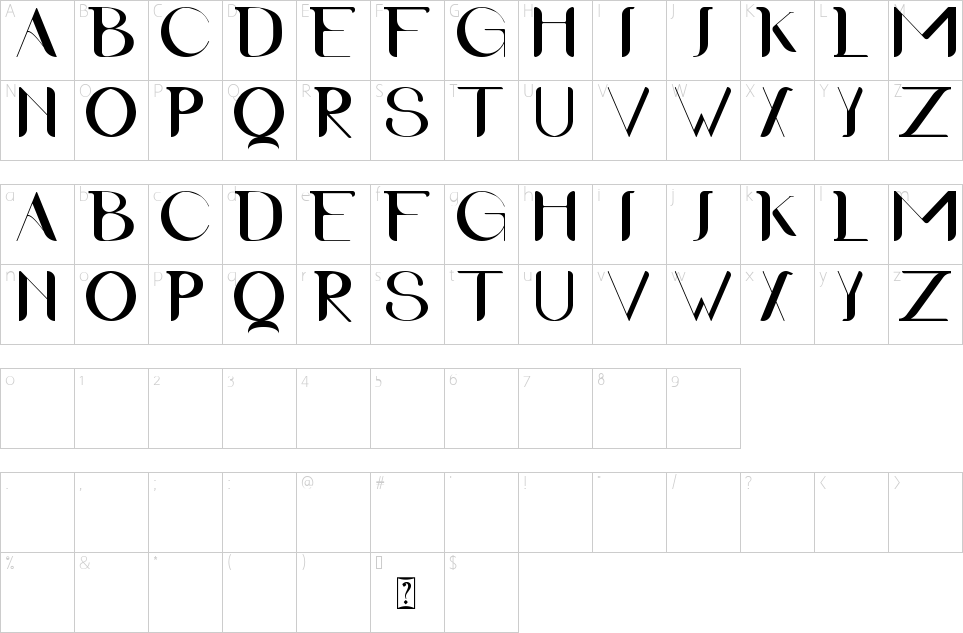
Calista Font
A Calista é uma fonte sem serif desenvolvida por Andang Prasetyo que se destaca pela sua elegância e facilidade na criação de textos profissionais. Com um design minimalista, ela oferece um equilíbrio perfeito entre alegria e seriedade, tornando-se uma excelente escolha para aplicativos tanto comerciais quanto acadêmicos. Suas linhas suaves e cânones leves permitem criar texturas e tipografias que destacam seu uso em qualquer contexto de design. A sua versão gratuita é ideal para desenvolvedores de sites e designers gráficos, oferecendo um poderoso conjunto de ferramentas para trabalhar com texto sem comprometer a qualidade do design final. Com apenas 2.536 downloads, essa fonte ainda está em fase experimental, mas sua qualidade faz dela uma opção muito promissora para quem busca uma fonte sem seria elegante e fácil de usar.